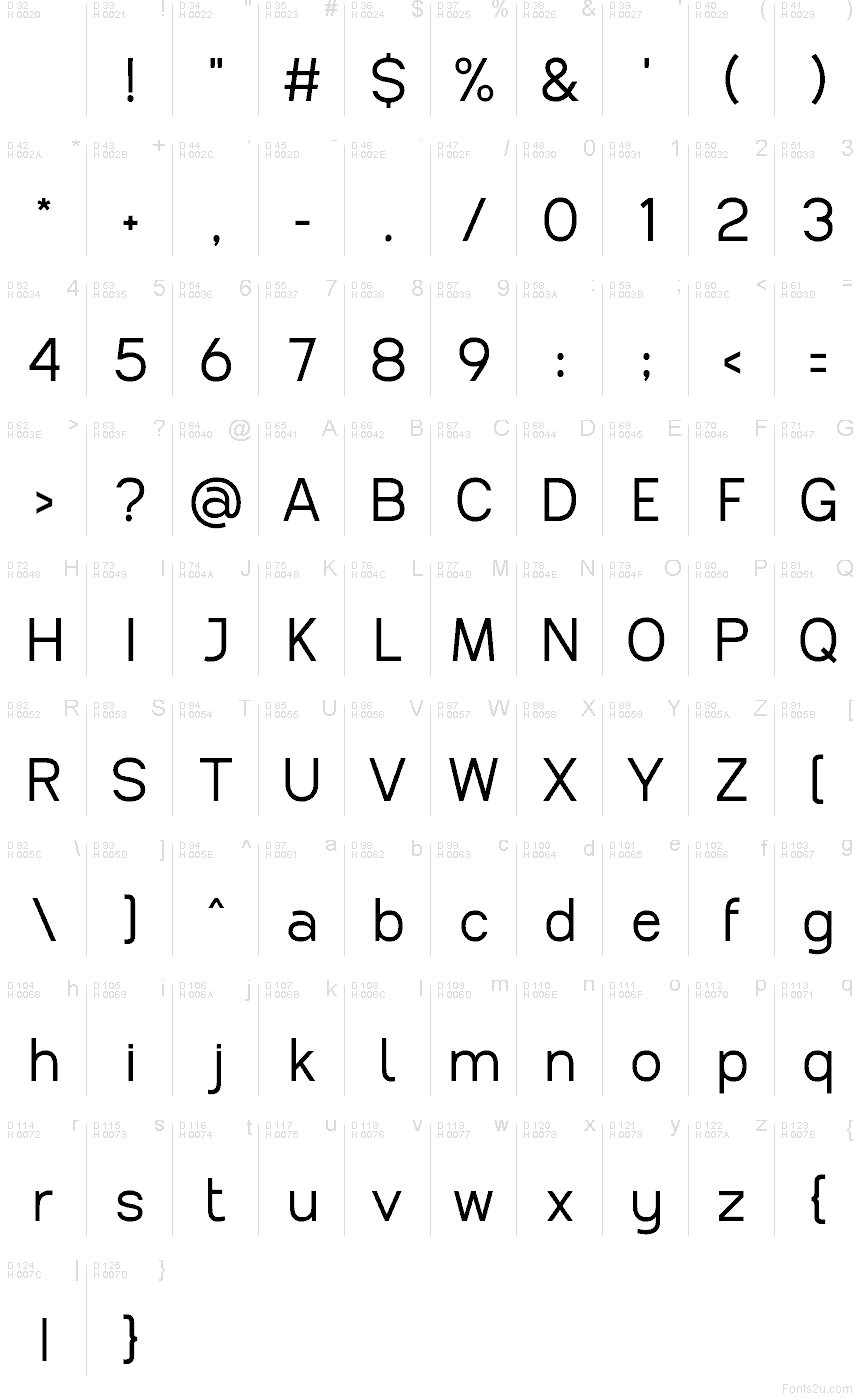
A Poltab Light da Glyphminds Studios é uma fonte sem serifa geométrica gratuita com um ritmo suave e amigável. As letras baseiam-se em formas quase circulares e junções fluidas, enquanto os traços altos e simples mantêm um visual moderno em vez de infantil, conferindo à fonte uma voz limpa com um toque humano delicado.
Ela adapta-se perfeitamente a branding, embalagens, cabeçalhos de aplicações, cartazes e gráficos para redes sociais onde se pretenda um visual contemporâneo sem arestas vivas. Sendo uma fonte gratuita, também faz sentido para títulos editoriais curtos, esboços de logótipos e etiquetas de interface, porque as formas arredondadas e o espaçamento aberto mantêm o tom calmo e acessível, mesmo em pequenos excertos de texto.